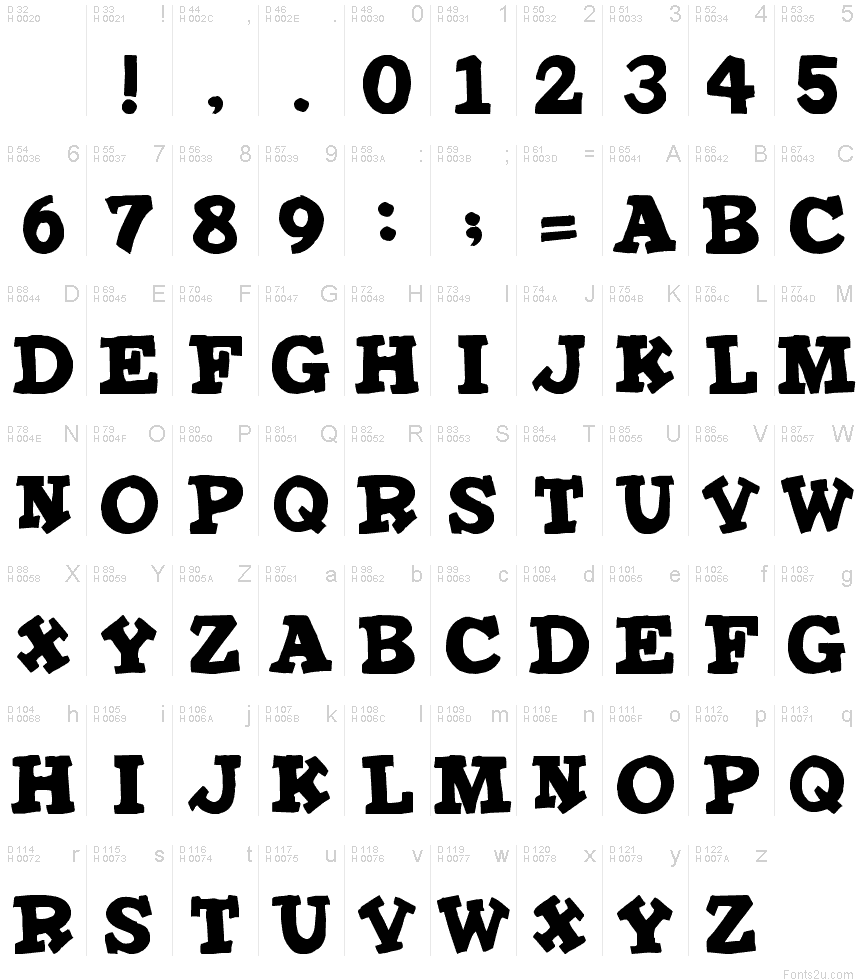
<p>IronMan od Jakoba Fischera to bezpłatny krój typu comic display, który oddaje ciężar i drżenie liter wyciętych w drewnie. Każdy znak wygląda jak odbity grubą warstwą farby, z masywnymi kształtami, nierówną szerokością i lekkim pochyleniem, dzięki któremu słowa na stronie wręcz krzyczą. Ta czcionka ma w sobie surową, namacalną energię – jest wystarczająco odważna, by przykuć uwagę, ale na tyle zabawna, by pozostać przystępną.</p>
<p>IronMan zapewnia wyraziste, uderzające liternictwo, które świetnie sprawdza się na okładkach komiksów, plakatach koncertowych, ulotkach na imprezy dla dzieci, naklejkach, zinach i w tytułach gier. Dzięki ciasnym odstępom i ciężkim formom krótkie frazy oraz duże nagłówki zyskują gęsty, mocny charakter. W przypadku tekstu głównego połącz ten darmowy font z czystym, lżejszym krojem bezszeryfowym, a IronMan używaj w dużym rozmiarze, aby jej surowa osobowość naprawdę wybiła się na ekranie lub stronie.</p>
IronMan